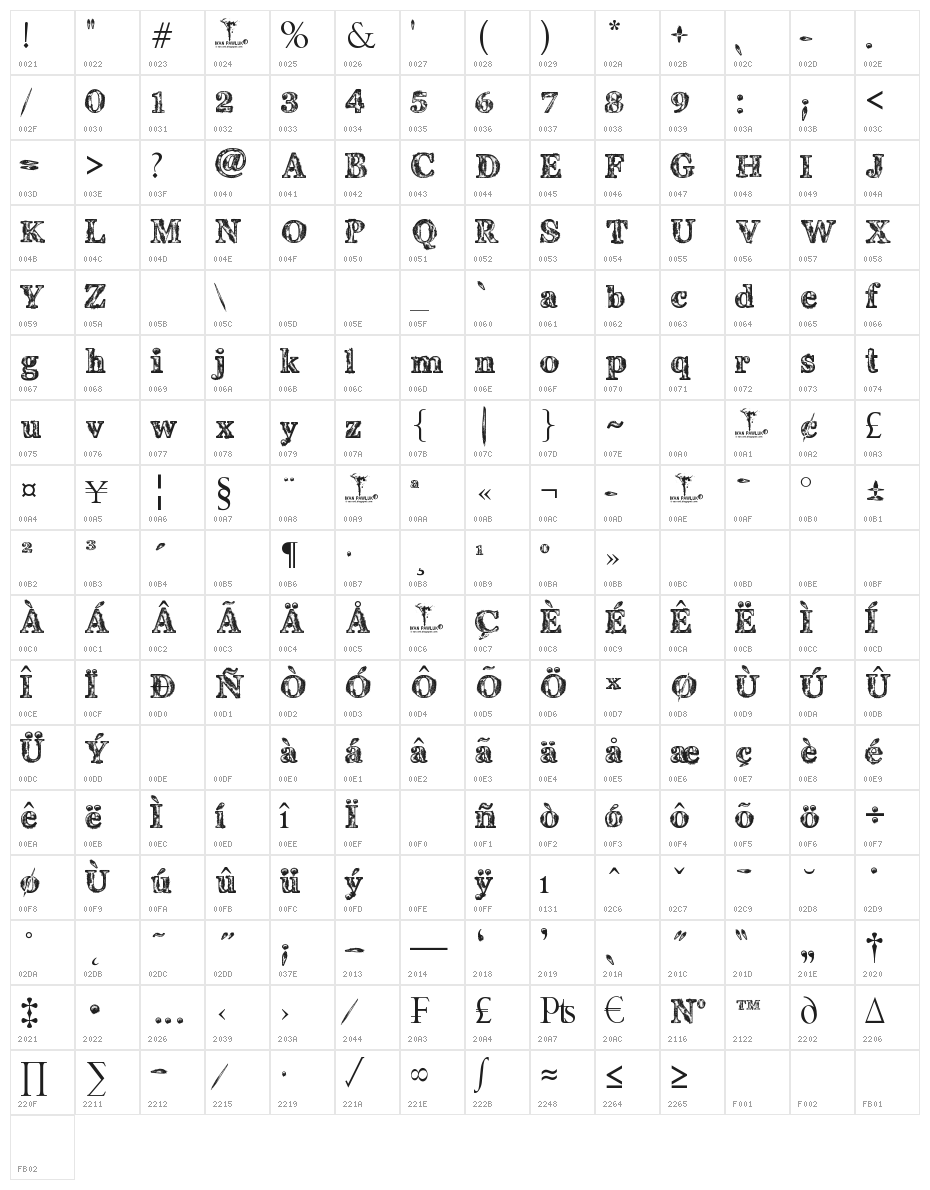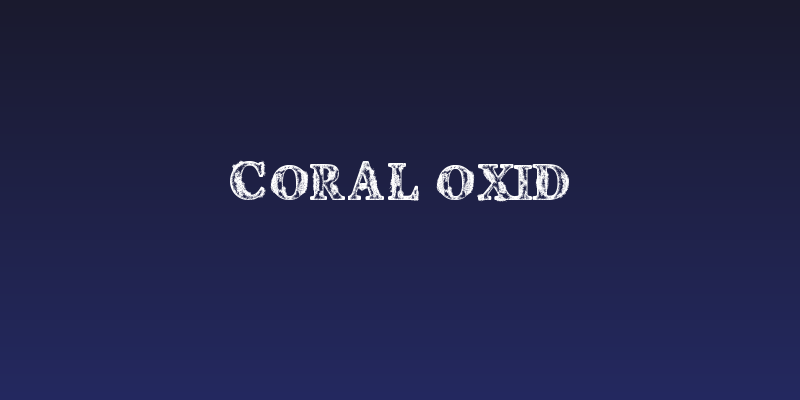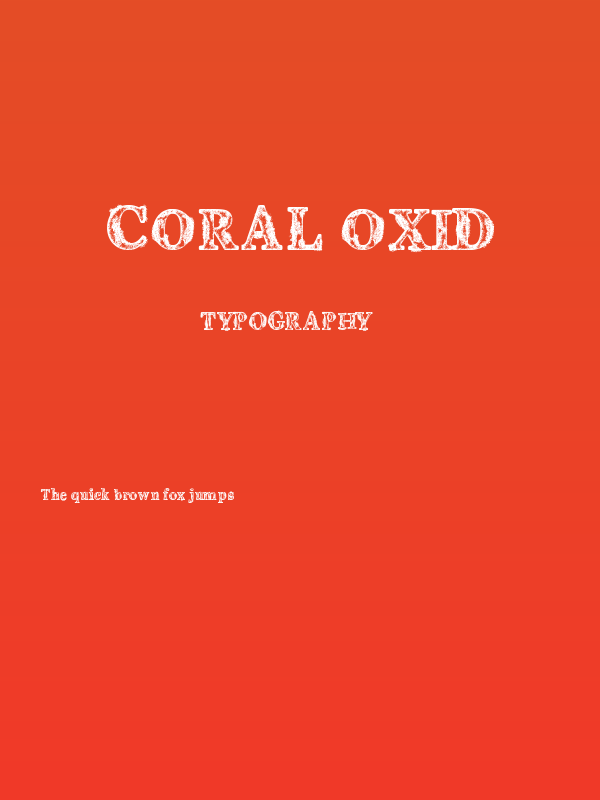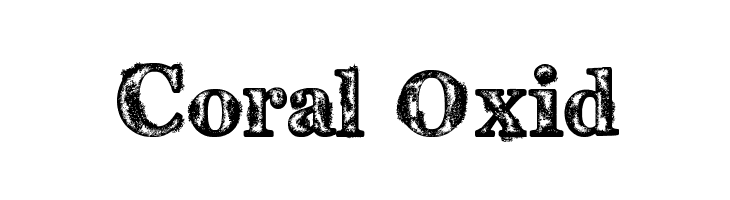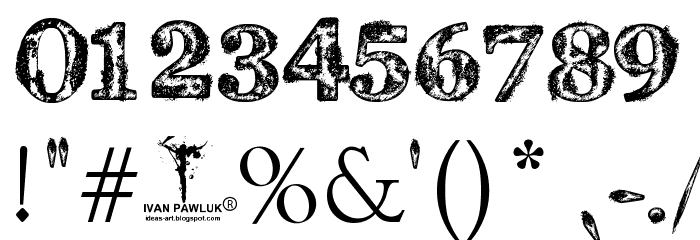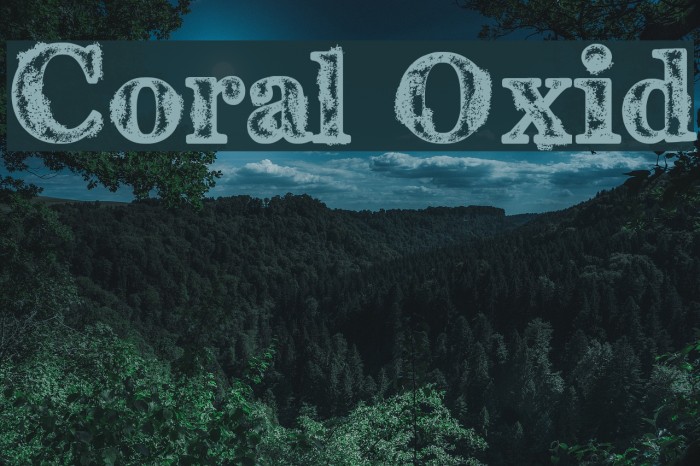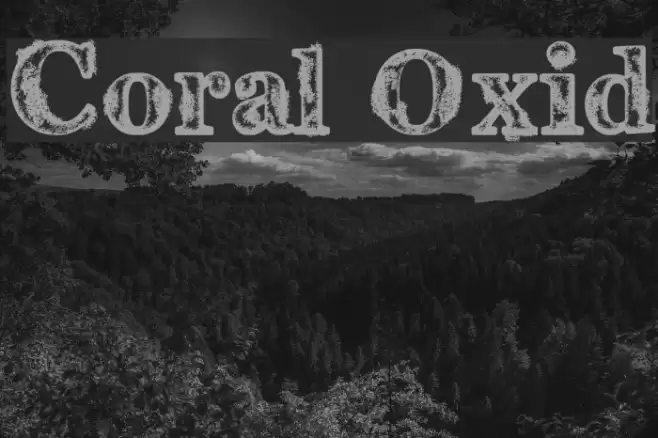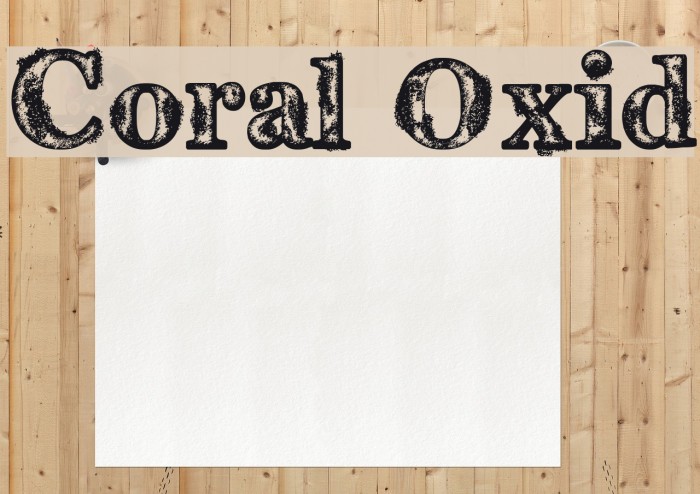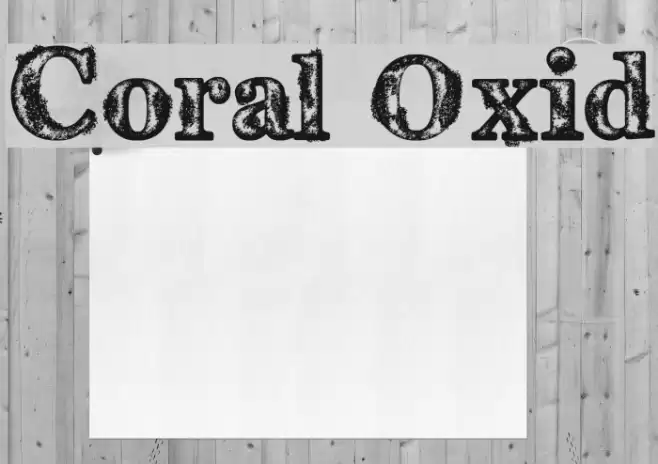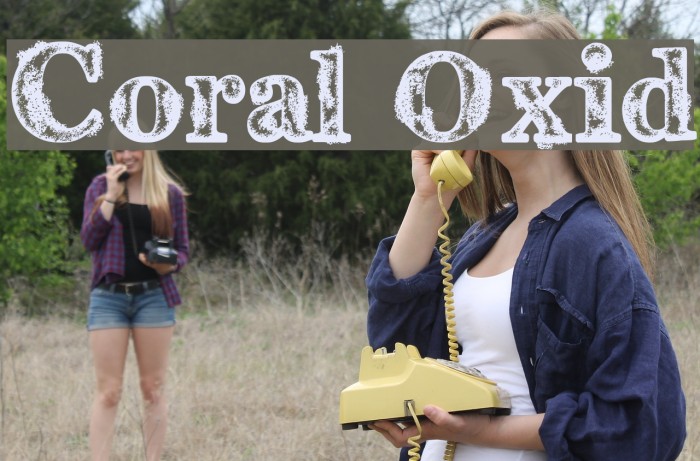
Coral Oxid Font
✎ Distorted Eroded
| おすすめプロジェクト | Ideal for vintage-themed posters, historical event flyers, rustic branding, and any project needing a touch of aged elegance. |